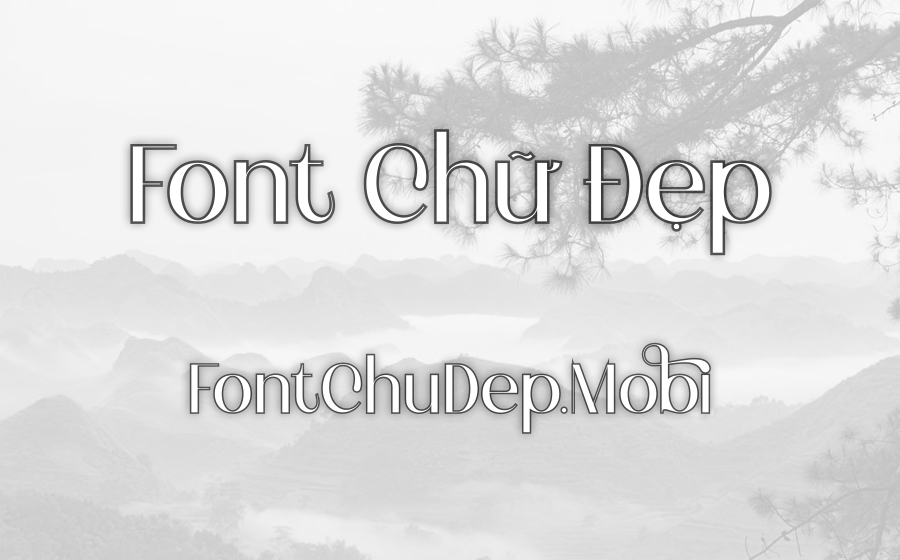
Font VL Begin Việt Hóa
VL Begin
Tên gọi VL-Begin của phông chữ serif có một sức hấp dẫn đặc biệt ngay từ lần đầu bạn sử dụng. Phông chữ này, do tài năng của nhà thiết kế Việt Linh sáng tạo, mang lại một dòng chảy hiện đại kết hợp cùng sự tinh tế. Các nét chữ của VL-Begin mảnh mai, uyển chuyển nhưng không kém phần mạnh mẽ, mang đến vẻ đẹp thanh lịch và tính chuyên nghiệp không thể phủ nhận cho mọi dự án thiết kế.
Điều đặc biệt mà VL-Begin mang lại là khả năng hỗ trợ đầy đủ các ký tự tiếng Việt, một yếu tố quan trọng giúp người dùng thoải mái triển khai ý tưởng sáng tạo. Hơn nữa, với sự sưu tầm và chia sẻ từ FontChuDep.mobi, phông chữ này đã trở thành sự lựa chọn lý tưởng cho những ai đang tìm kiếm một công cụ thiết kế đa dụng.
Để nói về ứng dụng của VL-Begin, đây thực sự là một lựa chọn hoàn hảo cho các tiêu đề, văn bản dài, thiết kế logo hay bất kỳ ấn phẩm in ấn nào khác. Đặc biệt trong các sự kiện như đám cưới, hội nghị hay các buổi lễ văn hóa, VL-Begin phát huy được khả năng tạo điểm nhấn ấn tượng. Không dừng lại ở đó, nó còn rất thích hợp trong các ngành thời trang, truyền thông và giáo dục nhờ vào thiết kế rõ ràng và thanh lịch. VL-Begin không chỉ là một phông chữ đơn thuần, mà còn là cách để bạn truyền tải thông điệp với sự sang trọng và tinh tế.